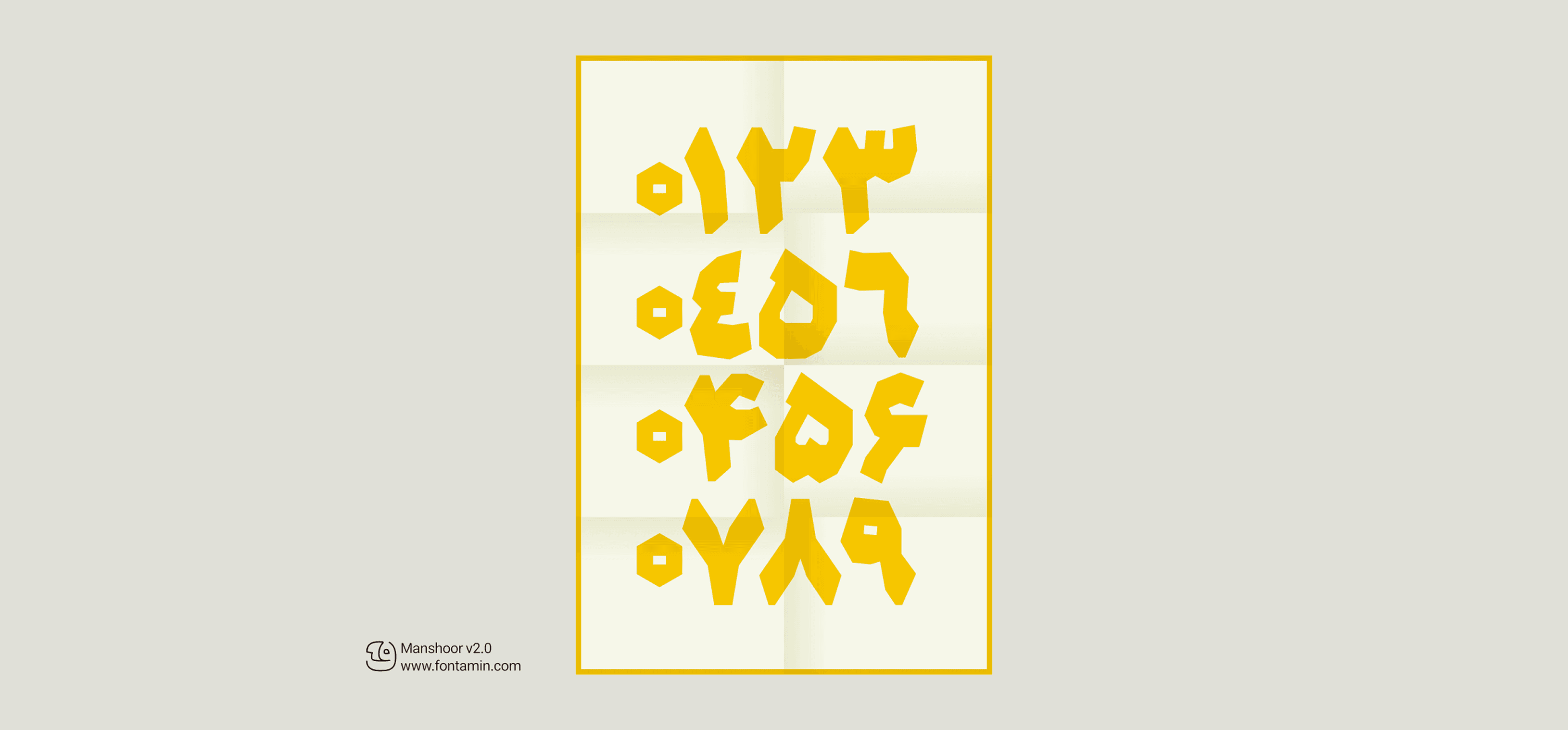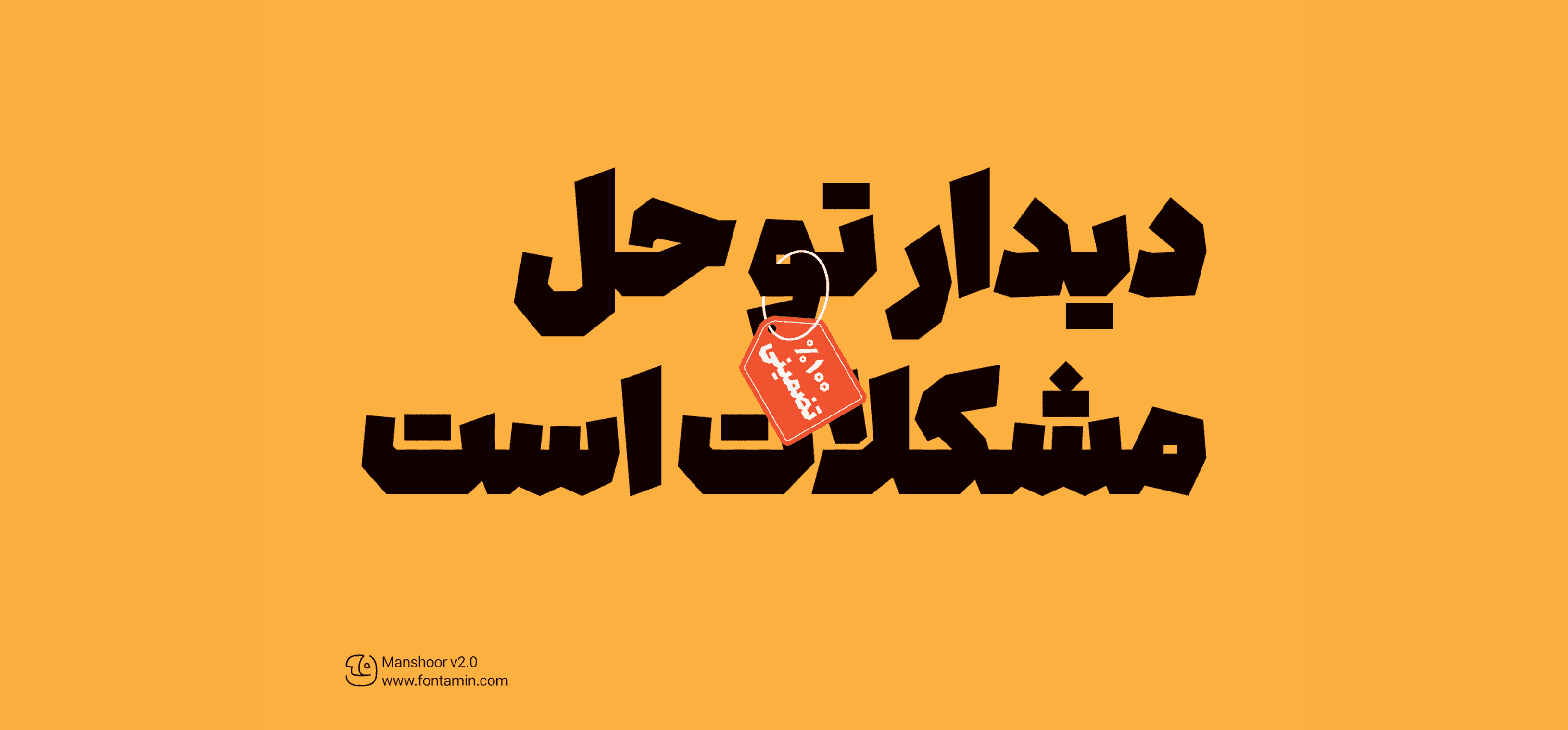
منشور یک تایپفیس با پنج وزن است که در طراحی تمام گلیفهای آن از خطوط مستقیم و بدون انحنا استفاده شده است.
در این فونت، تمامی تداخلات بهطور دقیق در بیشترین سطح اشباع کنترل شدهاند، و تنظیمات کرنينگ و فواصل حروف از بالاترین وزن آغاز شده و بهصورت تدریجی به وزنهای پایینتر انتقال یافتهاند.
در فرآیند طراحی حروف، تلاش شده تا علاوه بر رعایت اصول هندسی، از حرکت طبیعی قلم نیز تا حد ممکن الهام گرفته شود.